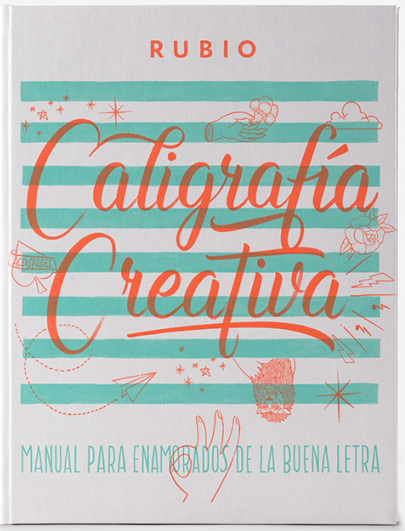
Seguramente a muchos de vosotros os acompañó durante vuestra niñez los famosos cuadernos de caligrafía Rubio. La editorial Rubio, fue creada hace más de 60 años por Ramón Rubio especializándose en la edición de cuadernos de caligrafía y de cálculo de los cuales llegaron a vender más de 300 millones de ejemplares.
En esta ocasión la editorial nos presenta una preciosa obra dirigida no tanto al público infantil como al adulto. Se trata de Caligrafía Creativa y en este caso no se trata de uno de los cuadernos típicos de la firma ya que estamos ante una obra encuadernada en tapa dura de tamaño generoso (A4) y de 150 páginas.
Y, como no podía ser de otra forma, sus páginas nos invitan a mejorar nuestra letra y a recorrer el camino que va de la caligrafía al lettering, de la letra escrita a la dibujada. Tran una introducción básica y pertinente, el libro nos propone en su primera parte empezar a ejercitarnos con las formas básicas para ir comprendiendo los secretos del contraste de los trazos y la presión para continuar con las letras y acabar con palabras que enlazan esas letras.
Poco a poco los ejemplos que nos propone el libro presentan una mayor complejidad y variedad que hace que la práctica sea también muy divertida y que nos van acercando hasta la segunda parte en la que nos encontramos con la letra dibujada y donde podemos encontrar ejemplos y consejos para conseguir composiciones espectaculares que sin duda os harán entrar en otro nivel y ver las letras de una forma completamente diferente.
La propuesta de Editorial Rubio nos parece un paso muy acertado para acercar la práctica de la caligrafía a otras generaciones y otros públicos tanto los que utilizaron sus famosos cuadernos como los que ven ahora una buena excusa para hacerlo.